خطوط احتفالية: أنماط متصلة للنسخ واللصق
تدور العطلات حول إضافة القليل من البريق الإضافي لكل ما تفعله. من تزيين منزلك إلى التخطيط للأزياء الاحتفالية، كل التفاصيل مهمة. فلماذا يجب أن تكون رسائلك الإلكترونية مختلفة؟ يمكن أن يبدو النص العادي والموحد باهتًا بعض الشيء عندما تحاول إضفاء جو من البهجة، أو خلق أجواء مخيفة، أو إرسال ملاحظة صادقة. إذا سألت نفسك يومًا، كيف أجعل نصي فاخرًا ومميزًا للمناسبات الخاصة؟، فأنت في المكان الصحيح.
مرحبًا بك في دليلك الشامل لاستخدام خطوط العطلات لرفع مستوى حضورك الرقمي. سواء كنت تصمم وصفًا مثاليًا على إنستغرام، أو دعوة رقمية، أو مجرد إضافة لمسة جمالية لرسالة ودية، فإن الخط المناسب يمكن أن يحدث فرقًا كبيرًا. باستخدام مولد الخطوط المتصلة القوي، يمكنك إنشاء نص جميل وملفت للنظر على الفور يمكنك نسخه ولصقه في أي مكان. دعنا نتعمق في كيفية جعل كل موسم مميزًا بأسلوب الخط المتصل المثالي.
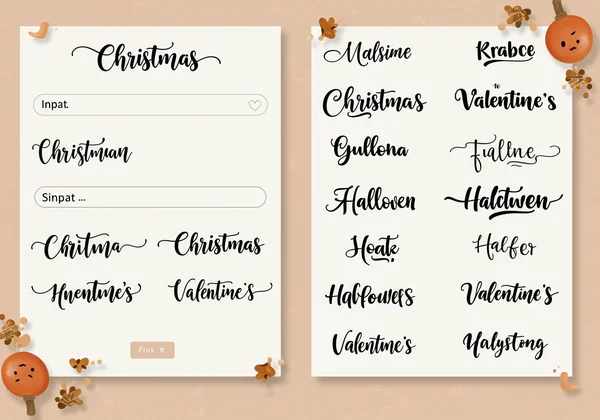
خطوط الكريسماس: أنماط احتفالية لرسائل عطلتك
عندما يحل ديسمبر، يمتلئ العالم بالدفء، والبهجة، ولمسة من السحر. يجب أن يعكس نصك ذلك! يمكن أن يؤدي استخدام خط كريسماس متخصص إلى تحويل "عيد ميلاد سعيد" بسيط إلى تعبير جميل عن روح العطلة. إنها الطريقة المثلى لجعل منشوراتك على وسائل التواصل الاجتماعي، وبطاقاتك الرقمية، ونشراتك الإخبارية العائلية تبدو احتفالية وفريدة من نوعها.
خطوط الكريسماس المتصلة الكلاسيكية للبطاقات والتعليقات
هناك شيء خالد حول الخط الأنيق والمنساب على بطاقة الكريسماس. يثير هذا الأسلوب مشاعر التقاليد، والدفء، والمشاعر الصادقة. فكر في الخط اليدوي الجميل على رسالة إلى سانتا أو بطاقة تهنئة كلاسيكية. تعتبر خطوط الكريسماس المتصلة الكلاسيكية هذه مثالية للتعليقات الأطول حيث تشارك قصة، أو تتمنى لمتابعيك عطلة سعيدة، أو ترسل بطاقة كريسماس رقمية للأصدقاء والعائلة. إنها تضيف لمسة من الرقي والإخلاص التي لا تستطيع الخطوط العادية مطابقتها.
خطوط متصلة مرحة وعصرية لإنستغرام وتيك توك
بالنسبة لخبراء وسائل التواصل الاجتماعي، الكريسماس هو وقت للمرح والمشاركة. يجب أن يكون محتواك جذابًا! أنماط الخطوط المتصلة المرحة والعصرية هي أفضل صديق لك لمنصات مثل إنستغرام وتيك توك. غالبًا ما تكون هذه الخطوط أكثر حيوية وجرأة وتصميمًا، مما يجعلها مثالية للنصوص القصيرة والمؤثرة على قصصك، أو مقاطع الفيديو القصيرة (Reels)، أو في ملفك الشخصي. تخيل "Ho Ho Ho!" بخط حيوي أو إعلان "مسابقة العطلة" بخط يصرخ بالإثارة. يساعدك استخدام مولد خطوط إنستغرام المناسب على إيقاف التمرير وجذب انتباه جمهورك على الفور.
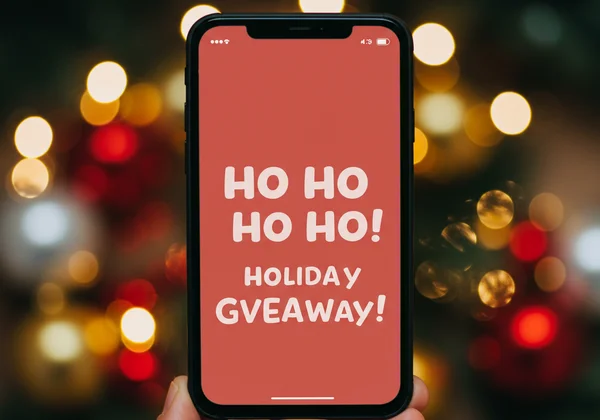
إنشاء بطاقات ودعوات كريسماس مخصصة
إذا كنت شخصًا مبدعًا يحب مشاريع "افعلها بنفسك"، فستعجبك هذه الميزة. أداتنا ليست فقط لوسائل التواصل الاجتماعي. يمكنك بسهولة تصميم ومعاينة النصوص لـ بطاقات ودعوات الكريسماس المخصصة. ما عليك سوى كتابة الاسم أو الرسالة، واختيار خط يتناسب مع موضوعك، وشاهد كيف يبدو. يمكنك حتى حفظ إبداعك كملف PDF، مما يجعله موردًا رائعًا لتخطيط تصميماتك قبل الطباعة. إنها طريقة سهلة لإنشاء مظهر متناسق واحترافي لجميع مشاريع عطلتك، من بطاقات الهدايا إلى دعوات الحفلات.
أنيق ومخيف: مولد خطوط الهالوين
مع تحول أوراق الشجر وازدياد برودة الجو، حان الوقت للانتقال من البهجة الاحتفالية إلى الأجواء المخيفة. يدور الهالوين حول الأجواء، ويمكن للخط المناسب أن يخلق مزاجًا مخيفًا تمامًا. سواء كنت تسعى إلى الأناقة القوطية أو المرح الكرتوني، يمنحك مولد خطوط الهالوين القدرة على تخصيص رسائلك لأكثر الأوقات رعبًا في العام.
أناقة غامضة: خط قوطي متصل للملفات الشخصية المسكونة
هل تريد أن تمنح ملفاتك الشخصية على وسائل التواصل الاجتماعي مظهرًا مسكونًا؟ الخط القوطي المتصل هو الخيار الأمثل. بفضل زواياه الحادة وسماته الدرامية، يضفي هذا الأسلوب على الفور لمسة من الأناقة الغامضة على نصك. إنه مثالي لتحديث ملفك الشخصي على إنستغرام أو تيك توك باقتباس مخيف، أو رسالة غامضة، أو ببساطة اسمك بأسلوب "مسكون". هذه الخطوط طريقة رائعة للدخول في الأجواء وإظهار لمتابعيك أنك مستعد للهالوين. أنشئ نص سير ذاتية مسكونة خاصًا بك haunted bios ببضع نقرات فقط.
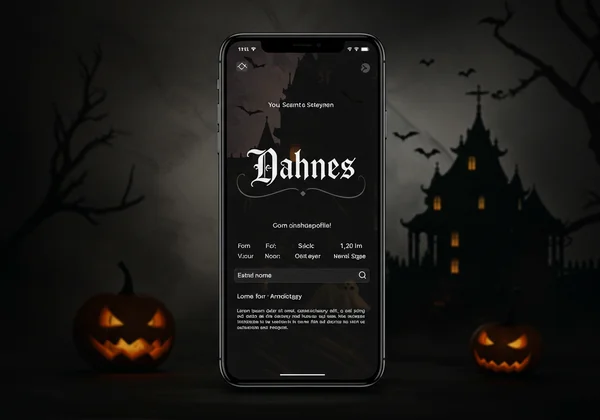
مرح وغريب الأطوار: خطوط كرتونية متصلة لدعوات الحفلات
لا يجب أن تكون جميع أجواء الهالوين مخيفة! إذا كنت تستضيف حفلة أو تحب الجانب الأكثر مرحًا من العطلة، فإن الخطوط المرحة والغريبة الأطوار هي خيار رائع. فكر في الخطوط التي تبدو وكأنها تنتمي إلى فيلم وحوش كلاسيكي أو كرتون أشباح ودود. هذا الأسلوب مثالي لدعوات الحفلات الرقمية، وإعلانات الأحداث على وسائل التواصل الاجتماعي، أو تعليقات ممتعة لصور أزيائك التنكرية. يمكن أن يجعل الخط الكرتوني المتصل المرح رسالتك أكثر جاذبية وإثارة للضيوف من جميع الأعمار.
حب ورومانسية: خطوط متصلة لعيد الحب
عندما يحل فبراير، يملأ الحب الأجواء. هذا هو الوقت المثالي لاستبدال الأنماط المخيفة بشيء أكثر رومانسية. يدور عيد الحب حول التعبير عن المودة، ويمكن لخط متصل أنيق أن يجعل كلماتك تبدو وكأنها مأخوذة مباشرة من رسالة حب كلاسيكية. إنها طريقة بسيطة لكنها قوية لجعل شريكك أو أصدقائك أو عائلتك يشعرون بالتميز الإضافي.
خط رومانسي: مثالي لملاحظات الحب والبطاقات الإلكترونية
يعد الخط الرومانسي الجميل والمنساب المعادل الرقمي للخط اليدوي المثالي في ملاحظة حب. هذه الخطوط رقيقة، وشخصية، ومليئة بالنعمة، مما يجعلها مثالية لصياغة رسائل رومانسية لشريكك المهم. استخدمها في منشور مخصص على وسائل التواصل الاجتماعي، أو رسالة خاصة، أو بطاقة إلكترونية رقمية مخصصة. يمكن أن تكون الرسالة الشخصية المكتوبة بخط جميل هدية لا تُنسى بحد ذاتها. حاول استخدام مولد أسماء الخطوط المتصلة لترى اسمك واسم شريكك بأسلوب جديد وجميل.
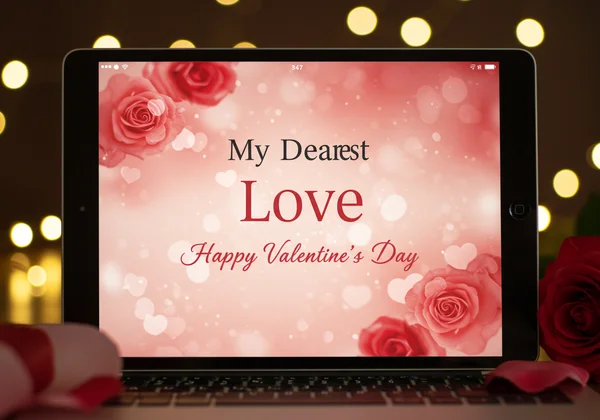
ما وراء العطلات الكبرى: أنماط نصوص احتفالية على مدار العام